Utilizzare caratteri nitidi su un desktop GNOME
Potresti aver notato che i caratteri sono piuttosto sfocati sui desktop Linux, il che può far male agli occhi se devi stare davanti al computer tutto il giorno. Il rendering dei caratteri è ancora un po’ scomodo ed è una delle ultime debolezze dei desktop Linux. Questo tutorial mostra come puoi far utilizzare caratteri nitidi a GNOME e a tutte le applicazioni GNOME (come Evolution, il browser di file Nautilus, ecc.). Infatti, utilizzeremo il carattere standard di Microsoft Windows, Tahoma, come carattere standard anche in GNOME, il che renderà il desktop piuttosto familiare se sei abituato a lavorare con un desktop Windows.
1 Nota preliminare
2 Confronto Prima - Dopo
Per darti un’idea di cosa otterrai, ti mostrerò le differenze con l’aiuto di alcuni screenshot nella loro dimensione originale (non li ho ridimensionati poiché ciò distorcerebbe la tua impressione).
Menu - Prima
Questo è l’aspetto dei caratteri nel menu ora:
Menu - Dopo
E questo è come appariranno dopo le tue modifiche. Come puoi vedere, i caratteri sono molto più nitidi, il che è meglio per i tuoi occhi. E come ulteriore vantaggio, se sei passato da un desktop Windows, ti sentirai a casa con il nuovo carattere poiché è il carattere Windows Tahoma:
Nautilus (Browser di file) - Prima
Nautilus (Browser di file) - Dopo
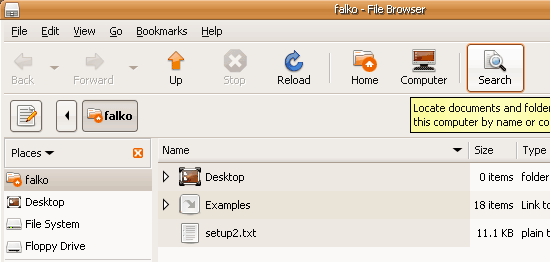
Tooltip - Prima
Tooltip - Dopo
Evolution - Prima
Evolution - Dopo